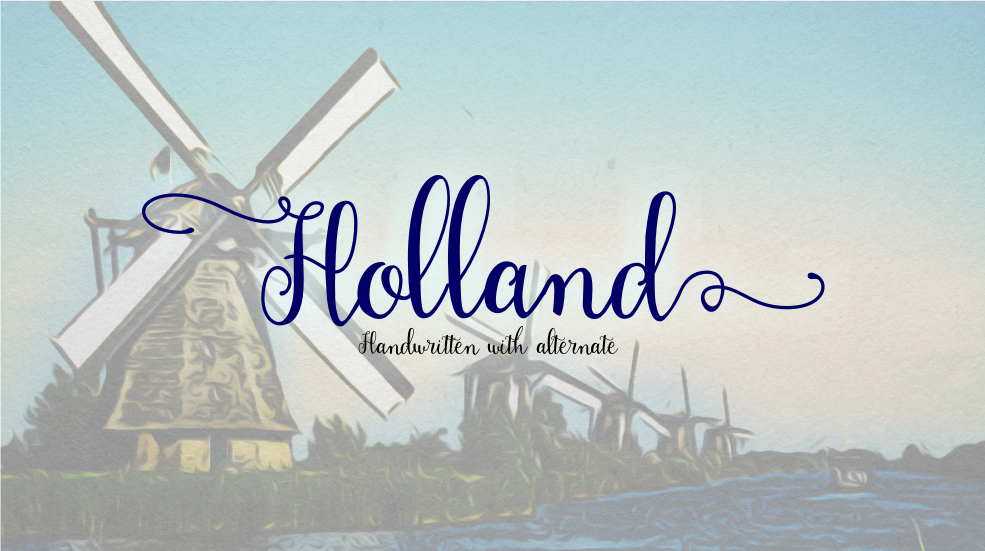
Holland Handwriting Font – Download Grátis
Esta fonte chamada Holland Handwriting é inspirada na escrita manuscrita tradicional encontrada nos velhos envelopes. Ela captura a essência do estilo antigamente usado, mas também traz uma sensação contemporânea e elegante que se sobrepõe à forma clássica da caligrafia de cobre. Holland Script é perfeitamente adaptável para uma variedade de aplicações visuais, desde cartões de convite até materiais de marca e posters. A fonte inclui letras maiúsculas e minúsculas, além de algumas das símbolos mais frequentemente utilizados no dia a dia. Holland Font é perfeitamente adequada para criar um visual elegante em vários tipos de mídia gráfica, proporcionando uma experiência envolvente e personalizada. Este design curvilíneo oferece um toque de graça ao texto, tornando-o ainda mais atrativo e sofisticado. Seja no design de cartas de convite ou na criação de materiais de marca empresarial, a Holland Handwriting certamente fará seu trabalho.